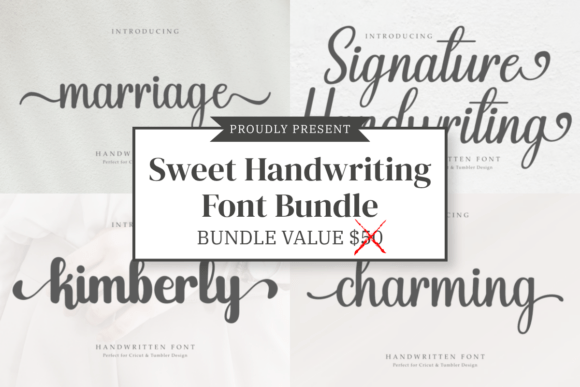
Sweet Handwriting
Trouver les bons éléments de conception peut être un défi, mais Sweet Handwriting propose une collection exceptionnelle qui rehausse instantanément votre travail.
Que vous créiez des produits POD (impression à la demande), des invitations de mariage ou des visuels pour les réseaux sociaux, Sweet Handwriting est un choix idéal.